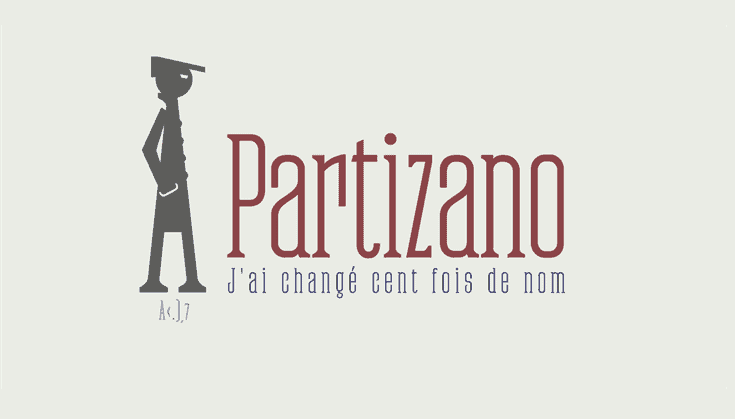
Partizano Serif Font – Fonte Grátis
Partizano Serif Font
A Partizano Serif é uma fonte serif que oferece um olhar elegante para o design editorial, publicitário e gráfico moderno. Com seu estilo retro geométrico extra condensado, ela proporciona espaços de texto muito eficientes horizontalmente em headlines e parágrafos, tornando-a ideal para ambientes onde você deseja uma tipografia exclusiva com grande economia de espaço. Essencial para o design gráfico avançado e publicações sofisticadas, a Partizano também abrange uma completa gama de letras maiúsculas, números e símbolos monetários em minúsculas. Além disso, oferece alternativas como as letras ‘A’ capital e ‘a’ em minúscula tipo alpha. Para aqueles que precisam escrever o simbolo Bitcoin ou a icon Partizano específico, basta pressionar os seguintes teclados: b # e a #. A fonte foi criada pelo designer defharo para profissionais de design, oferecendo um toque sofisticado e único em seus trabalhos.